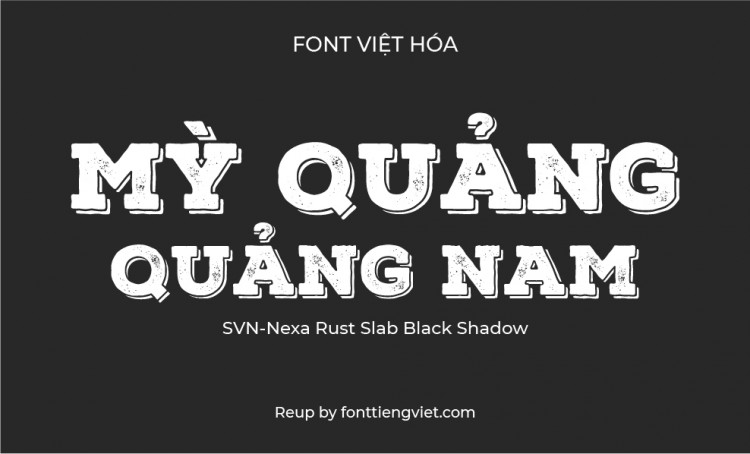
Font việt hóa SVN Nexa Rust Slab Black Shadow
Giới thiệu về Font việt hóa SVN Nexa Rust Slab Black Shadow
Trong thế giới đồ họa hiện đại, việc lựa chọn Font Miễn Phí phù hợp đóng vai trò quyết định đến sự thành công của một dự án. Font việt hóa SVN Nexa Rust Slab Black Shadow là một trong những bộ phông chữ độc đáo nhất thuộc hệ sinh thái Nexa Rust nổi tiếng. Với phong cách Slab Serif kết hợp hiệu ứng đổ bóng Shadow đầy ấn tượng, bộ font này mang lại vẻ ngoài mạnh mẽ, thô mộc và đậm chất cổ điển (vintage). Đặc biệt, bản việt hóa giúp các nhà thiết kế tại Việt Nam dễ dàng sử dụng trong các ấn phẩm truyền thông mà không lo lỗi font hay thiếu ký tự đặc trưng.
Đặc điểm nổi bật của Font việt hóa SVN Nexa Rust Slab Black Shadow
Thiết kế thô mộc đầy cá tính
Đặc trưng lớn nhất của Font việt hóa SVN Nexa Rust Slab Black Shadow chính là những đường nét góc cạnh, mô phỏng bề mặt in ấn thủ công cũ kỹ. Hiệu ứng Black Shadow giúp các con chữ trở nên nổi bật, tạo chiều sâu thị giác cực tốt cho người xem. Đây là lựa chọn hoàn hảo cho các tiêu đề lớn, banner quảng cáo hoặc logo mang phong cách Retro.
Tính ứng dụng linh hoạt trong đời sống
Dù có vẻ ngoài hầm hố, nhưng phông chữ này vẫn đảm bảo tính dễ đọc và thẩm mỹ cao. Bạn có thể sử dụng font này để thiết kế bìa sách, menu quán cà phê, áo thun hoặc các dự án nghệ thuật cần sự phá cách. Khả năng tương thích tốt trên nhiều phần mềm đồ họa như Photoshop, Illustrator hay Canva khiến nó trở thành công cụ đắc lực cho mọi người dùng.